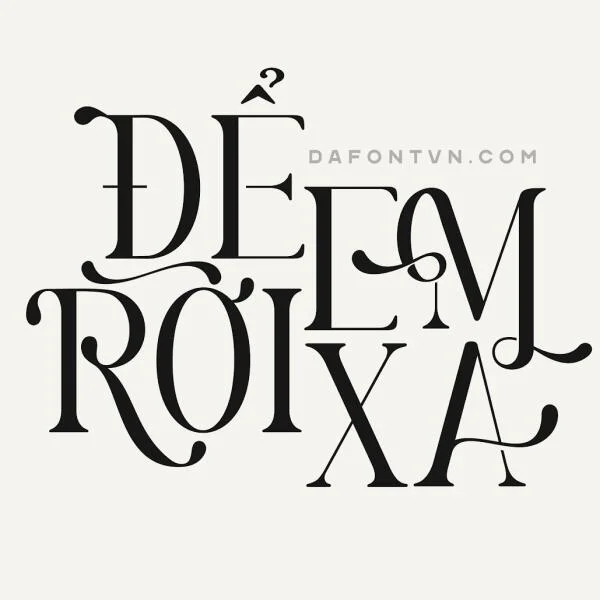
Tải font chữ vintage việt hóa theo phong cách xưa cũ
Tổng quan về font chữ vintage
Đây là một kiểu font mang phong cách vintage lấy cảm hứng từ những biển hiệu thời xưa mình đã việt hóa font với các dấu theo phong cách xưa cũ. Với kiểu chữ cứng cáp mang một chút cổ điển này rất phù hợp để sử dụng cho rất nhiều các thiết kế khác nhau như tiêu đề, tạp chí, biển hiệu, quảng cáo...
Font chữ vintage xưa cũ việt hóa
Mẫu 1
font chữ thời bao cấp việt hóa
Mẫu 2